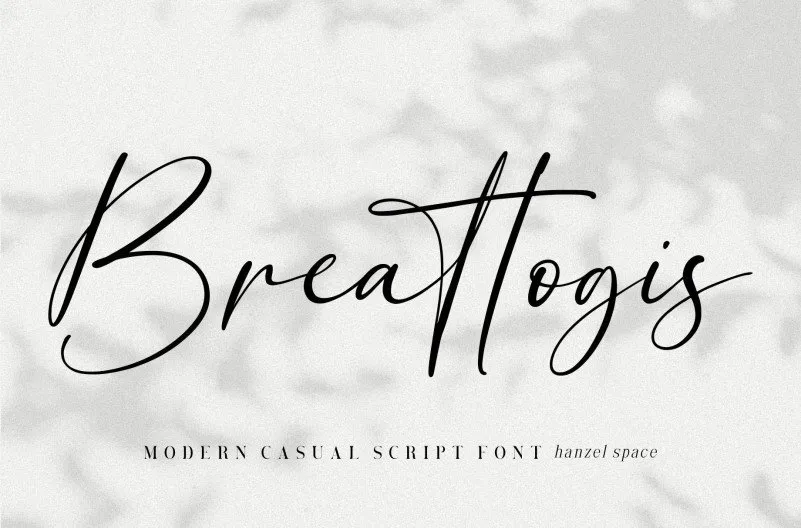
Breattogis Handwritten Font – Fonte Grátis
Breattogis Handwritten Font
A Breattogis Handwritten Font é uma escolha perfeita para aqueles que buscam um estilo elegante e contemporâneo para seus projetos digitais. Com seu fluxo natural e sofisticado, essa fonte foi criada por Hanzel Space, designer de fontes no site 99designs. Ela oferece uma combinação perfeita de modernidade e elegância, tornando-se a escolha ideal para criações que incluem branding, invitations de casamento, slogans e cartões de visita. A Breattogis é também uma ótima opção para aplicar em rótulos ou logotipos, fornecendo ao seu design um toque único e sofisticado que certamente destacará seus elementos. Este fonte ideal é perfeitamente adaptável a um vasto número de usos criativos, garantindo que sua obra prima tenha um visual memorável e profissional.